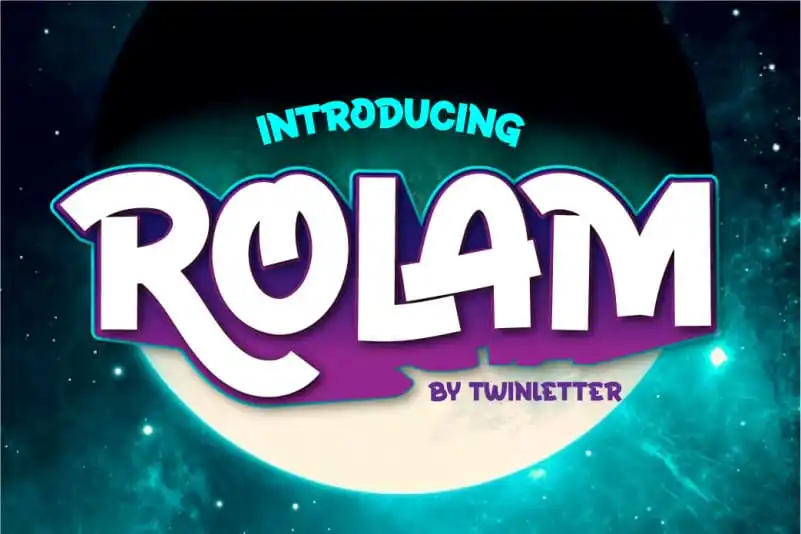
Rolam Display Font – Download Grátis
A “Rolam Display Font” é uma elegante escolha para aqueles que buscam um estilo forte e moderno em seus projetos de design. Com características sólidas, assertivas e claramente definidas, ela consegue brilhar em qualquer projeto visual, seja ele em cartazes, logotipos ou materiais de mídia digital. Ideal para criar uma identidade visual distintiva que chama a atenção dos olhos, esta fonte é perfeita para designers buscando um elemento diferenciador em seus trabalhos. Seja você criando uma marca empresarial, produzindo material publicitário ou desenvolvendo conteúdo digital, a “Rolam Display Font” oferece a clareza e a força necessárias para deixar sua marca na tela.